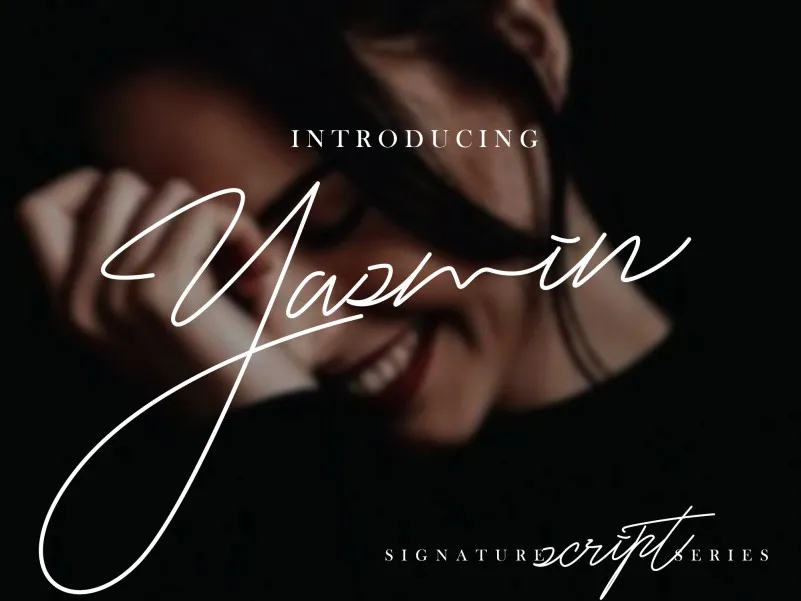
Yasmin Free Script Font – Download Grátis
A Yasmin é uma fonte escrita a mão leve, delicada e misteriosa. Suas extraordinárias variações nos contornos dão-lhe um toque fascinante e único, tornando-a ideal para aplicar em projetos de marca ou anúncio. Este é o tipo de detalhe que transformará qualquer projeto, fazendo-o parecer mais autêntico e sofisticado. Yasmin é perfeitamente adaptada às criações gráficas envolventes, tornando-a uma escolha excelente para designers buscando adicionar um toque especial a seus projetos. Com ela na sua disposição, você pode capturar o espírito delicado de Yasmin e trazer vida à qualquer projeto em que use. Não importa se é um logo, um banner ou um design editorial – Yasmin pode ajudá-lo a destacar-se da concorrência com um toque único e misterioso.